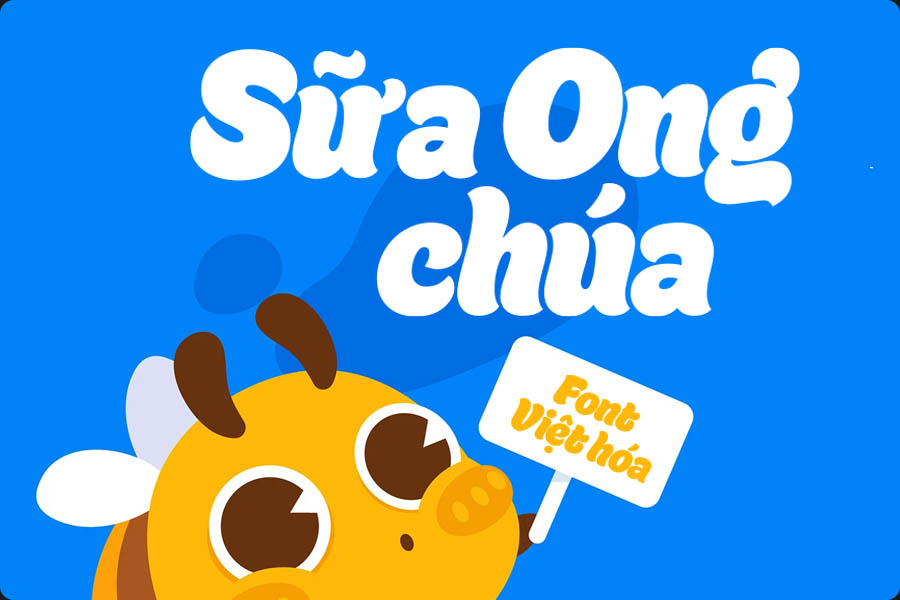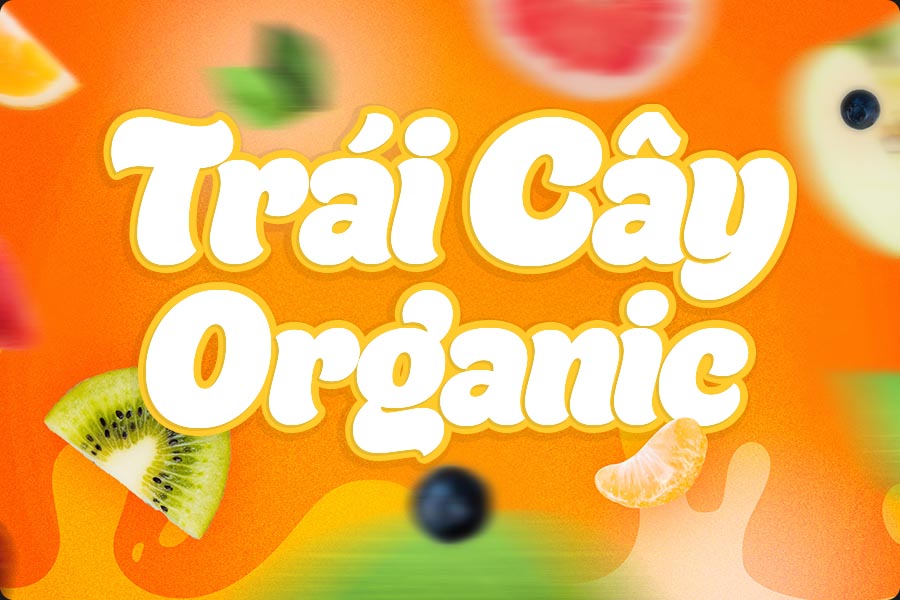
Font chữ hoạt hình béo tròn đẹp Việt hóa TH Ekamai
Font chữ TH Ekamai là phiên bản Việt hóa của font gốc Ekamai, một kiểu chữ script brush vui nhộn được thiết kế bởi Dave Rowland (Eclectotype Foundry). Bản Việt hóa được thực hiện bởi đội ngũ S99.VN, giúp phông chữ tương thích hoàn toàn với tiếng Việt. TH Ekamai thuộc nhóm font hoạt hình béo tròn, mang phong cách vui nhộn, gần gũi và thích hợp với nhiều ứng dụng dành cho trẻ em hoặc thương hiệu dễ thương.
Đặc điểm thiết kế nổi bật của TH Ekamai
Font TH Ekamai được phát triển theo phong cách script brush, mang đậm tinh thần viết tay nhưng có sự tiết chế về độ nghiêng và góc cạnh để dễ ứng dụng trong thiết kế hiện đại. Các đường nét của font được xử lý rất kỹ: độ dày đồng đều, khoảng cách chữ được cân đối tốt và các đường cong uốn mềm mượt nhưng không bị rối mắt. Từng ký tự đều mang vẻ tròn trịa, mượt mà, giúp tạo ra cảm giác vui tươi và thân thiện ngay từ cái nhìn đầu tiên. Điều này khiến TH Ekamai trở thành lựa chọn lý tưởng cho các thiết kế cần gợi sự ấm áp, dễ thương, đặc biệt trong các sản phẩm hướng đến trẻ em hoặc thương hiệu thiên về cảm xúc.
TH Ekamai có phù hợp với thiết kế tiếng Việt không?
Câu trả lời là hoàn toàn phù hợp. Phiên bản Việt hóa do S99.VN thực hiện đã xử lý toàn bộ hệ dấu tiếng Việt một cách tỉ mỉ: từ dấu sắc, huyền, hỏi, ngã cho đến dấu mũ, trăng đều được căn chỉnh hài hòa với từng con chữ. Không chỉ hỗ trợ đầy đủ ký tự Unicode, TH Ekamai còn hiển thị rất ổn định trên hầu hết các phần mềm đồ họa phổ biến như Photoshop, Illustrator, Canva và cả PowerPoint. Đây là ưu điểm vượt trội so với nhiều font quốc tế khác vốn thường thiếu glyph hoặc không tương thích hoàn toàn với tiếng Việt. Nhờ đó, bạn có thể yên tâm sử dụng font này cho mọi dự án sáng tạo bằng tiếng Việt mà không phải mất công chỉnh sửa thủ công.
Tổng kết
Tóm lại, TH Ekamai là sự kết hợp hoàn hảo giữa phong cách viết tay tròn trịa, vui nhộn và khả năng ứng dụng cao. Với bản Việt hóa đầy đủ từ S99.VN, đây là lựa chọn tuyệt vời cho mọi thiết kế hướng đến trẻ em và sự thân thiện.